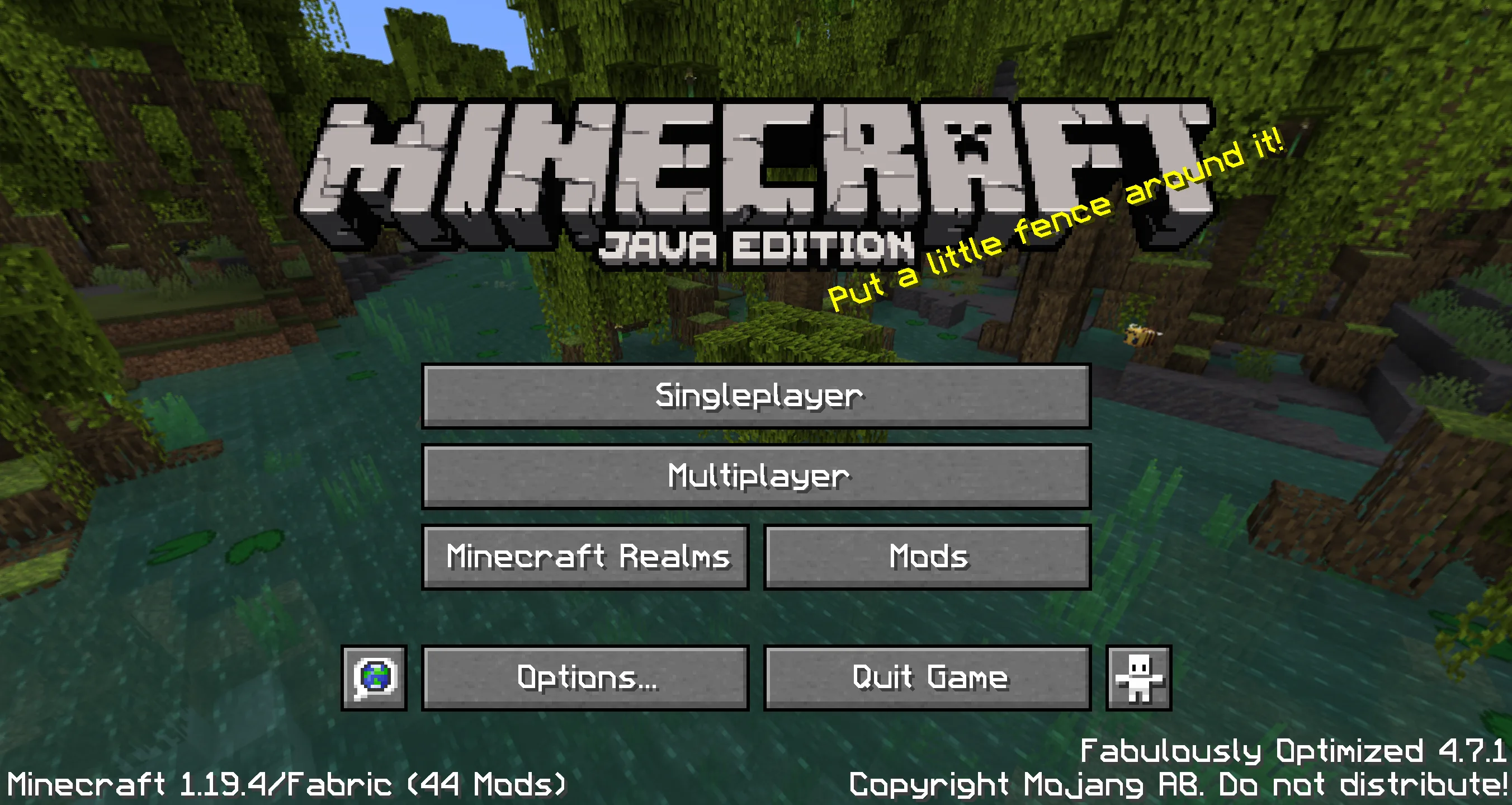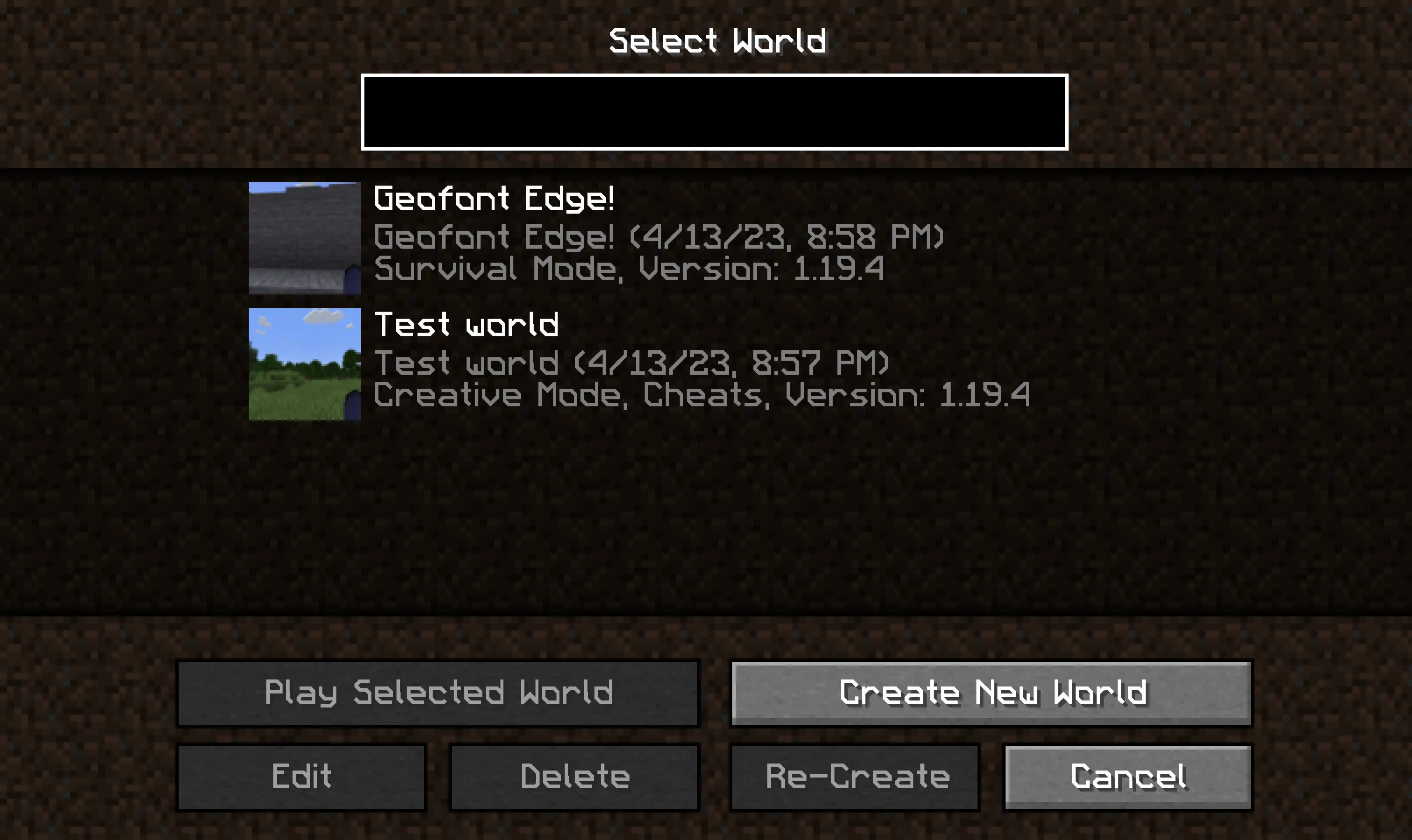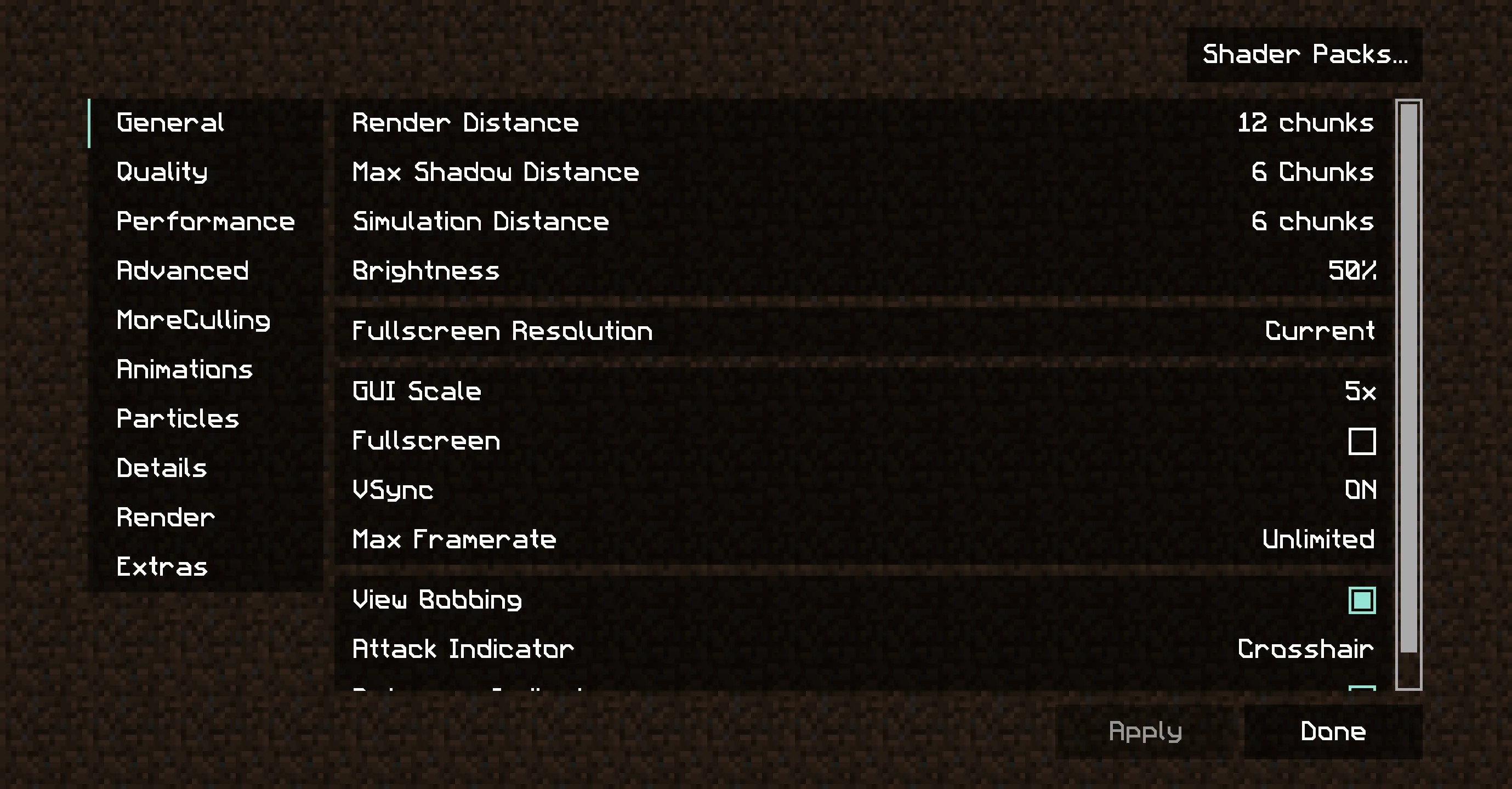
Geometric Font Edge
Геометрический шрифт Edge — это более резкая версия GeoFont с элементами научной фантастики, подходящая для ванильного Minecraft.
Этот ресурспак предлагает геометрический шрифт с острыми краями и элементами научной фантастики, который хорошо сочетается с ванильным стилем Minecraft. В отличие от многих других HD-шрифтов, использующих растровые изображения, этот шрифт не искажается при изменении масштаба интерфейса.
GeoFont Edge — это полностью переработанная версия оригинального шрифта с полной поддержкой OpenType и усиленной стилизацией для ещё большей резкости. Научно-фантастическая эстетика отлично смотрится как в чистом Minecraft, так и в сочетании с современными или футуристическими интерфейсами.